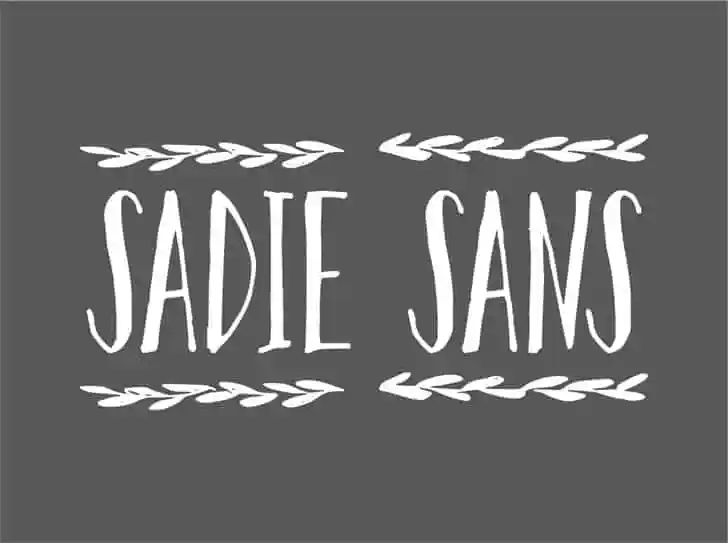
Sadie Sans Font – Download Grátis
A fonte “Sadie Sans” foi projetada à mão por PetroVivier e é apaixonadamente batizada em memória do seu cão de estimação. Esta elegante escolha de fonte é perfeita para uso em logomarcas, subtítulos e até mesmo postais, oferecendo um toque único e criativo a qualquer projeto gráfico. A fonte possui um estilo despojado, que combina perfeitamente com os elementos da designer, resultando em uma identidade visual amigável e envolvente. O download inclui um par de ícones para logomarcas, criando um layout completo e sofisticado para seus trabalhos gráficos. O design cuidadoso da fonte deixa seu projeto se destacar de forma agradável e divertida sem perder sua importância. Seja em uma campanha publicitária ou num mural de rua, “Sadie Sans” é um recurso gráfico que certamente deixará suas impressões inesquecíveis.